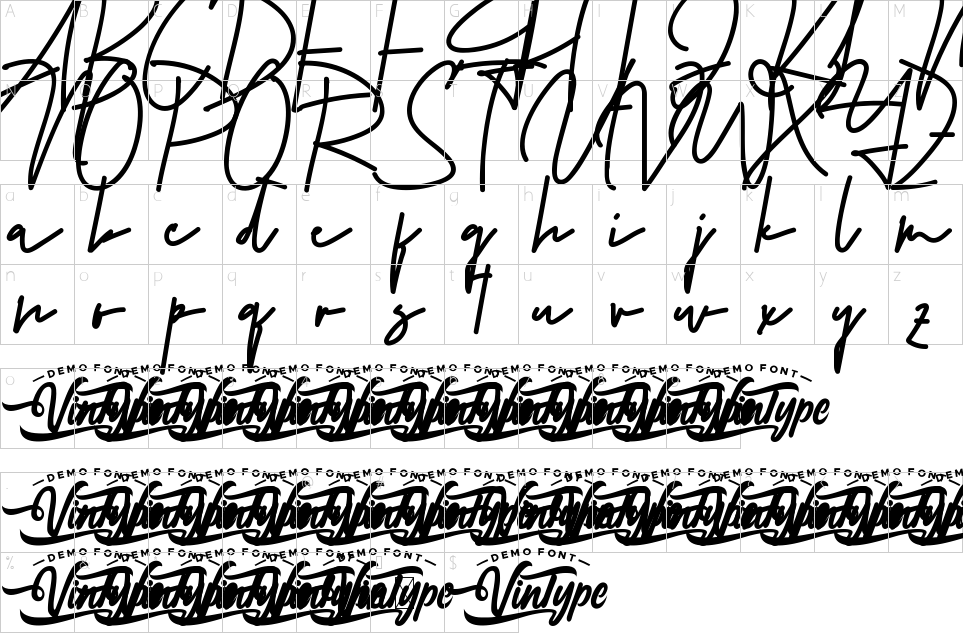
A fonte James William é uma escolha ótima para quem procura um design elegante e minimalista, ideal para criar materiais profissionais sem custos. Desenhada pelo VinType, a fonte James William está disponível gratuitamente tanto no sistema operacional Windows quanto no Mac. Esta seleção de 1001 Free Fonts é uma maneira perfeita de adicionar um toque único e sofisticado às suas criações digitais sem gastar nada. Seja para projetos pessoais ou profissionais, a James William oferece linhas leves e elegantes que permitem a escrita clara e profissional. Para quem está sempre buscando recursos de design gratuitos, esta fonte é uma ótima escolha – ela permite-lhe criar materiais impecáveis sem ter que se preocupar com custos adicionais. Através da fonte James William você pode adicionar um toque único e sofisticado a qualquer projeto digital. Seja para um site de negócios, um portfolio pessoal ou até mesmo para os fins pessoais – esta é uma excelente maneira de fazer isso sem ter que gastar dinheiro extra. Além disso, o fato de ser gratuita também significa que você pode testá-la e descobrir melhor como ela se adequa a seus propósitos específicos sem riscos significativos.